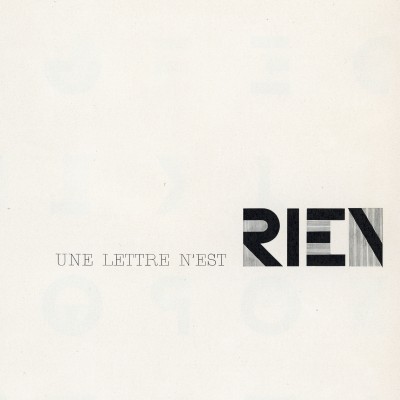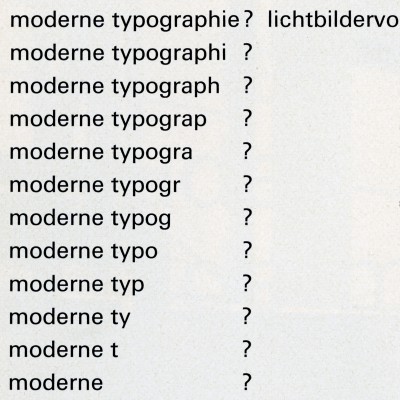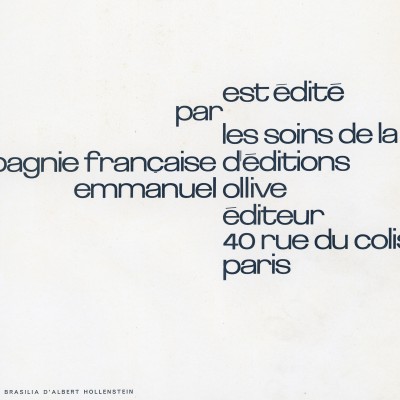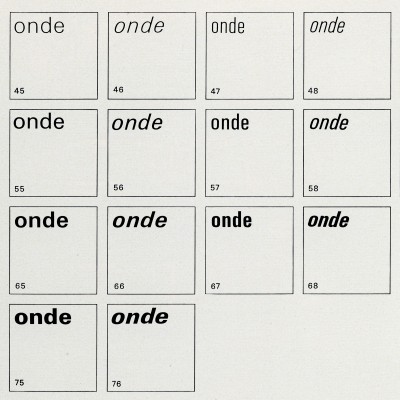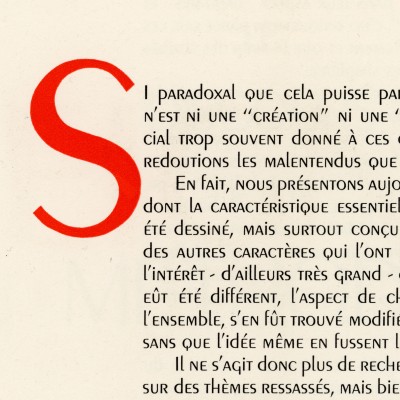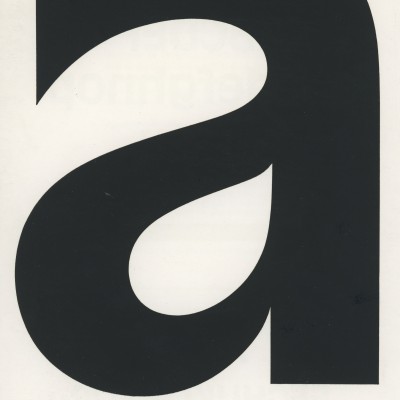
Le chantier thématique dédié à la typographie développe une histoire contextuelle des échanges entre Suisse et France par le biais de quatre cas d’études couvrant l’histoire du dessin de police typographique et leur migration ou rejet au sein des scènes francophones dans les deux périodes. En particulier, des études par le dessin sont développées pour comprendre la généalogie des polices objets de la recherche.
● Futura/Europe et Bifur : une modernité française
Détail du spécimen du Bifur, conçu par A. M. Cassandre, publié par la Fonderie Deberny et Peignot, 1929.
● Deberny & Peignot versus Fonderie Olive
Détail du spécimen de l’Antique Olive, conçu par Roger Excoffon, publié par la Fonderie Olive, années 1960.
Détail du spécimen du Peignot, conçu par A. M. Cassandre, et publié par la Fonderie Deberny & Peignot, 1937.
● L’Univers des Suisses de Paris
Détail d’un spécimen conçu par Emil Ruder pour le caractère Univers, publié dans la revue Typographische Monatsblätter (nº1, 1961).
Détail d’une carte d’invitation conçue par Emil Ruder, reproduite dans la revue Typographische Monatsblätter (nº1, 1961), et utilisant le caractère Univers d’Adrian Frutiger, publié par Deberny & Peignot en 1956.
● Une pratique mixte : Studio Hollenstein
Détail d’une page de la revue Caractère Noël, présentant le caractère Brasilia d’Albert Hollenstein, 1960.